不可不知的版面编排小秘诀
作为平面设计师,除了要跟客户打交道以外,更多的是和文字、图片、图形等,编排元素打交道。如果,将版面比喻为画布的话,那它们就是我们用来作画的工具,正所谓:工欲善其事必先利其器。要想画好,首先我们就要学会使用这些工具。而今天的这篇文章将跟大家分享,使用“工具”的技巧与方法。我会按照从整体到局部的思维,依次讲解它们在版面中的,设定方法与用途。希望大家在看完这篇文章后,能对编排设计有一个全新的认知与了解。
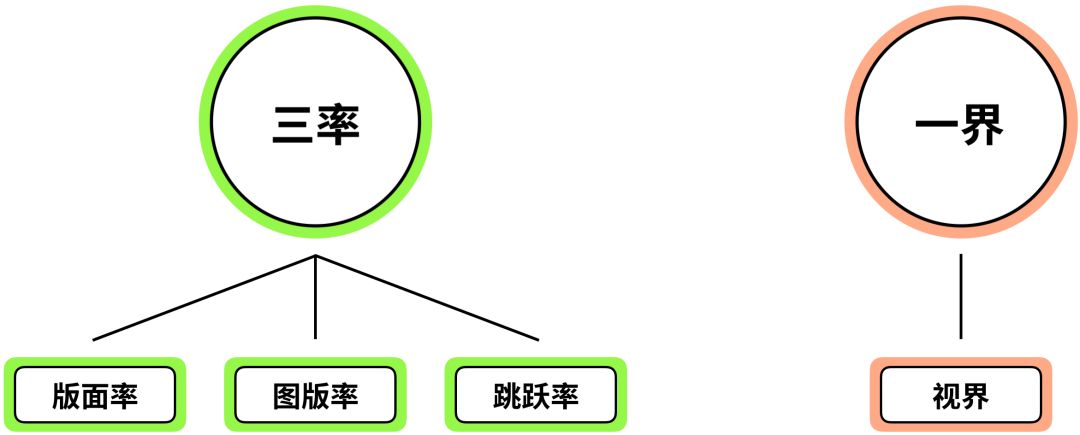
在平面设计中,有三率一界的说法。三率指的是版面率、图版率以及跳跃率,而一界指的是视觉界限,简称视界。今天不谈一界,主要来说说三率。
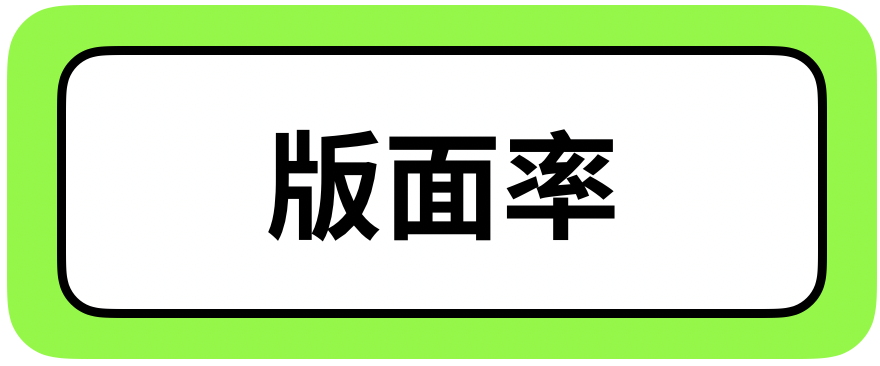
首先来了解一下,什么是版面率。版面我们都知道,是用来承载信息的一个载体。
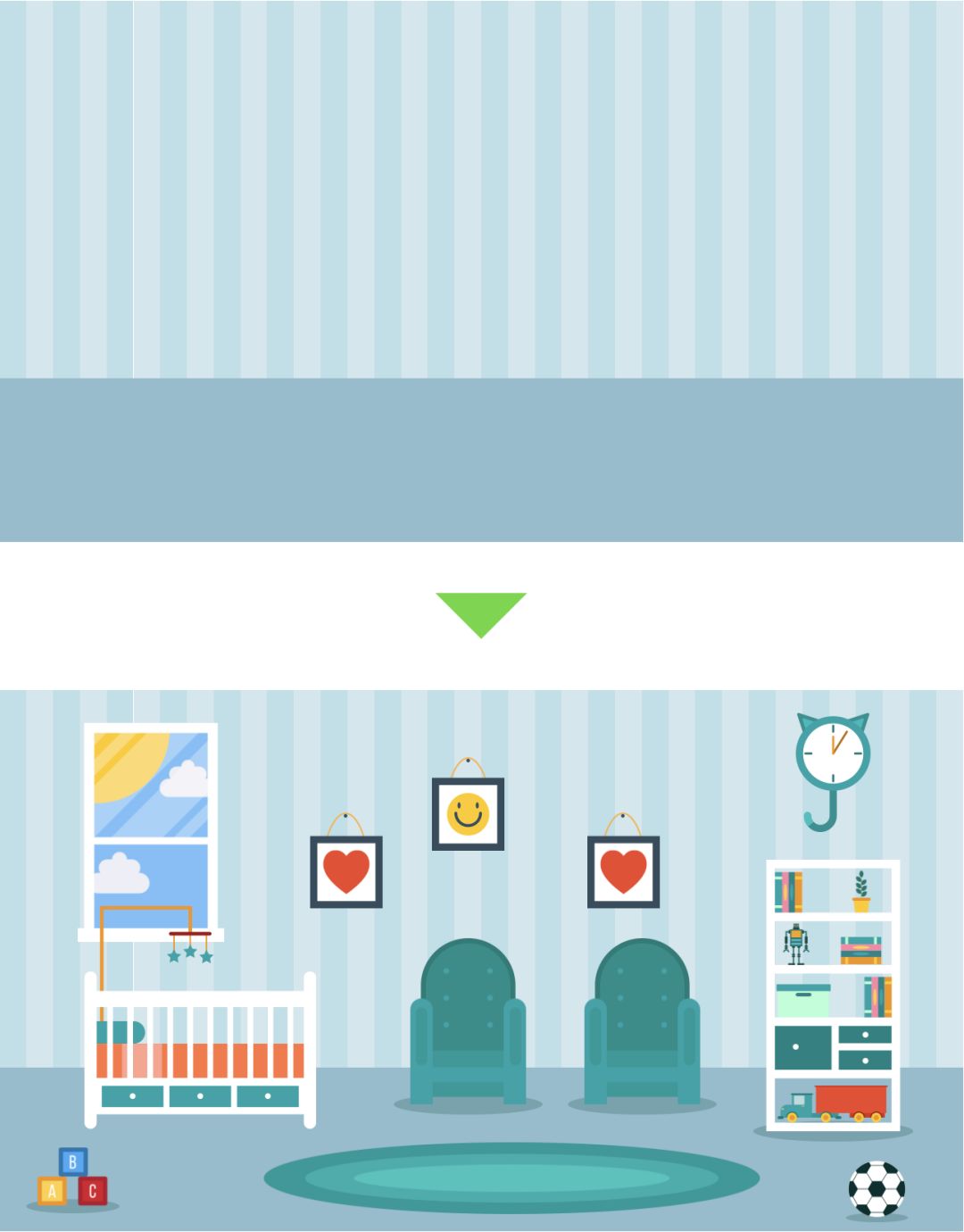
它就像是一个房间,而文字信息与图片素材,则是家具饰品。在合理的情况下,这个房间内放的东西越多,物品占据房间的面积比例也就越高,整个房间的空间被利用的也就越充分。
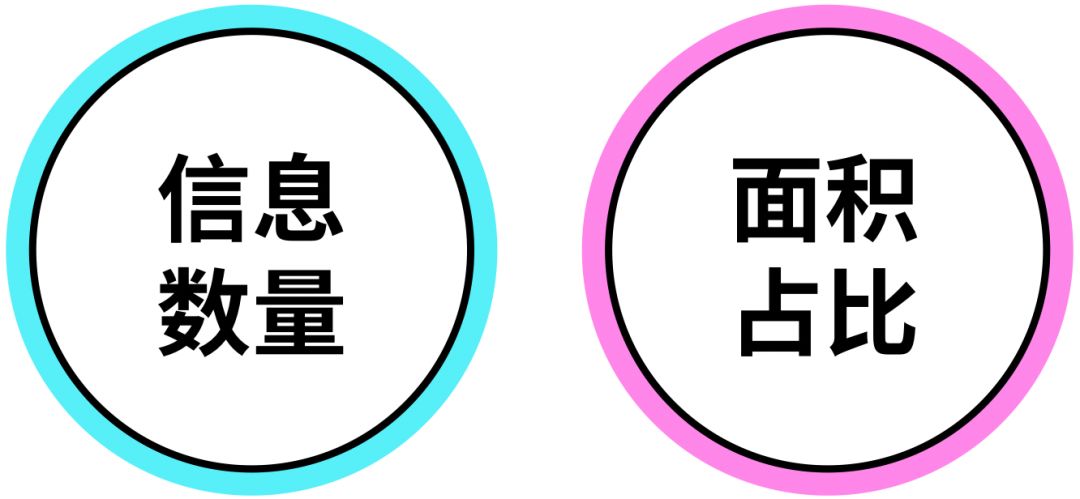
判断一个版面的版面率是高还是低,我们就看版面内部的,信息数量与元素的面积占比即可。
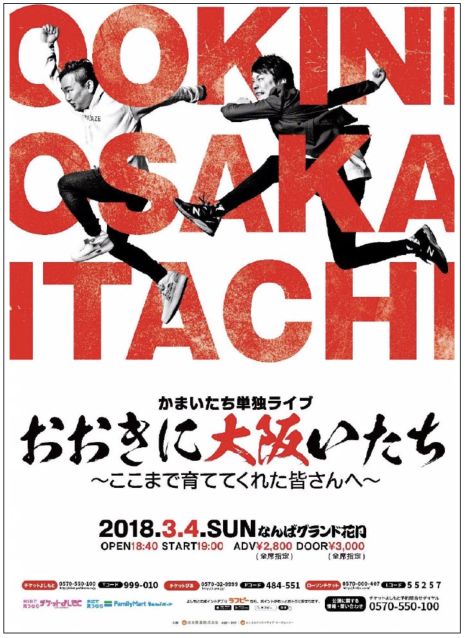
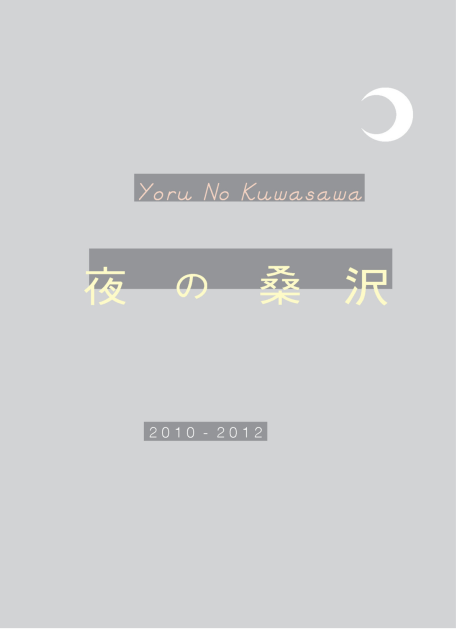
信息量越多,元素的面积占比也就越高,相对的版面率也就越高。信息量越少,元素的面积占比也就越低,相对的版面率也就越低。
不过,数量也不是,唯一的评价标准,关键还得看这些信息,在版面当中的面积占比,为什么这么说呢?
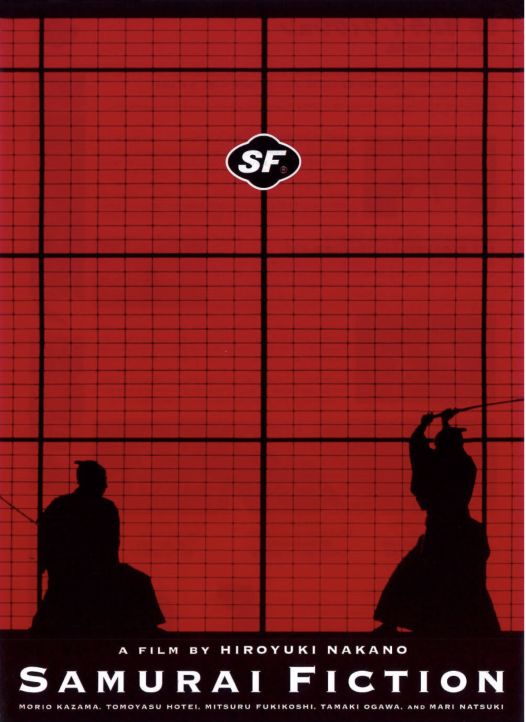
因为,当信息量不多时,只要元素的面积占比够大,版面率依然不会受到影响。跟信息量多的版面比,它们的版面率都是一样的。
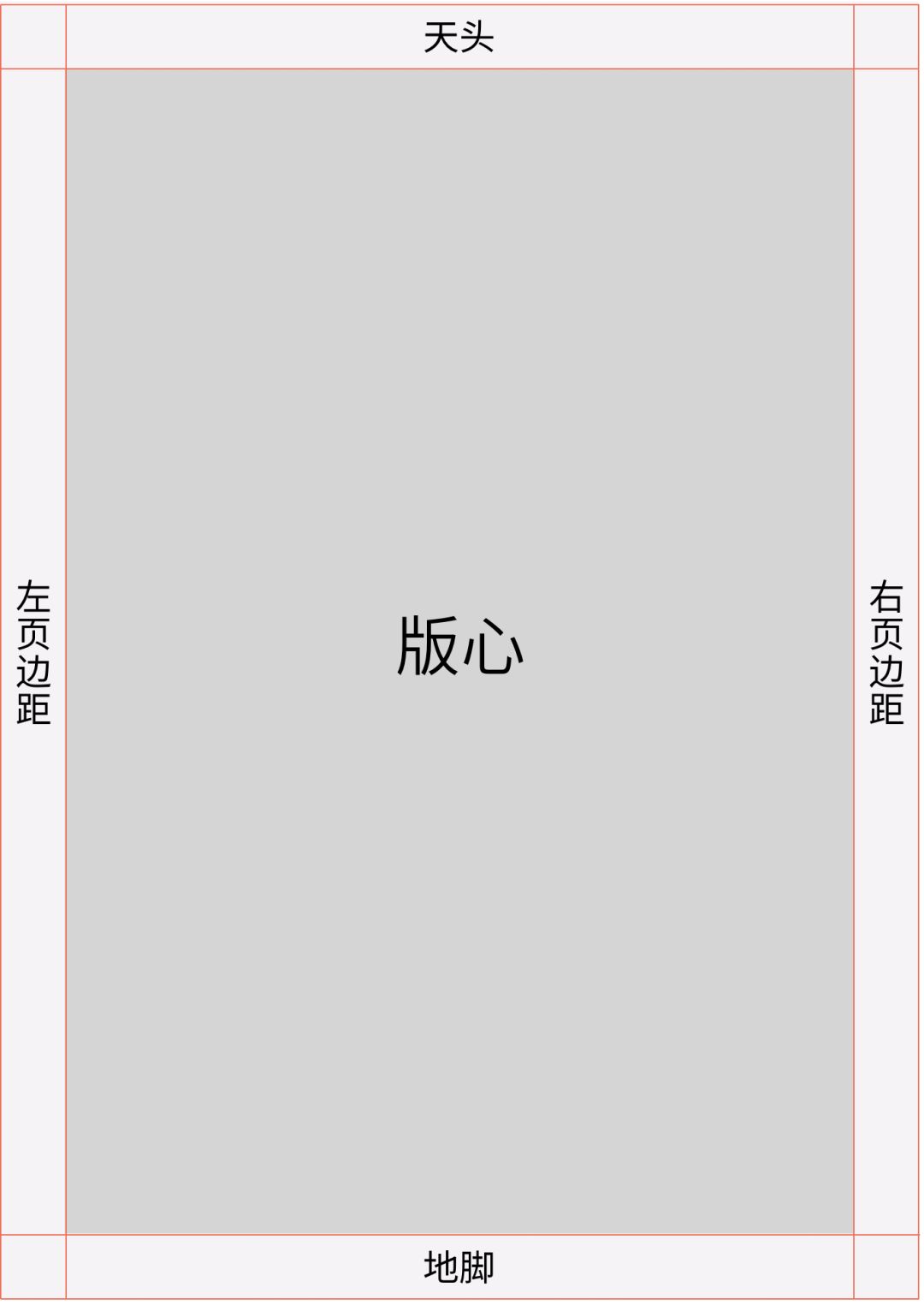
我们都知道,一个版面是存在版心的。除去天头地脚,左右页边距外,剩下的空间就是版心所在的区域了。
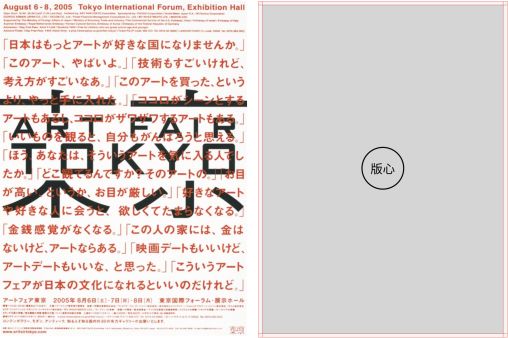
版心的大小会直接影响到,版面率的高低。因为之前也说过了,版面好比是一个房间,你拿一个40平米的房,跟80平米的房比承载量的话,结果可想而知。
除了版心以外,对版面率影响最大的,要数留白了。哪怕你版心定得再大,如果版面内部留白较多的话,版面率还低的。因为留白与元素的面积占比,是成正比的。留白多,元素的面积占比就少,留白少,元素的面积占比就多。
在版心一致的情况下,留白越少版面率越高,留白越多版面率越低。
除了有版面留白以外,还有图片留白。相较于常规的图片来说,那些为了表现清新、安静的图片,会刻意的创造留白来迎合氛围。
在版面率一致的情况下,跟图片留白少的版面比,图片留白多的版面,版面率会显得较低。
版面率越高,画面的视觉张力就越大,版面也会表现的更加活泼与热闹
反之,版面率越低,画面给人的感觉则非常典雅与宁静,版面也会更有格调。
版面率之所以有高低之分,完全取决于你想要传达的气质是什么。当需要表现出,活泼与热闹感时,可以提高版面率。当需要表现出安静、典雅范时,则可以降低版面率。
图版率和版面率的意思相近,版面率说的是,文字与图片占据画面的比例,而图版率说的是,图片占据画面的比例。
如果整个页面都是由图片构成的,那图版率就是100%。反之,如果页面全是文字,图版率则为0%
一般来说,版面中的图片数量越多,图版率也就越高。因为随着图片数量的增加,图片的占比也在增加。
但有一点需要注意的是,跟版面率一样,元素的数量并不是绝对的。要想图版率高,在有数量的基础上,图片自身的面积也不能过小。
哪怕版面中只有一张图片,只要面积足够大的话,图版率给人的感觉,也会比那些数量上占优势的版面要高。
一般来说,图片的视觉冲击力比文字强85%,提高图版率可以活跃版面,但完全没有文字的版面也会显得格外空洞,让人觉得这个版面非常的单调与无味。
当图版率为0%时,观者会丧失阅读的兴趣,因为版面显得非常枯燥。当图版率为40%时,观者的阅读兴趣会随之上升,因为版面充满了生气,富有活力。当图版率为100%时,版面则会给观者带来,强烈的视觉感受。
看到这,我相信不用分析大家也知道了,图版率高的版面,会给人带来活跃与热闹的印象。
相反,图版率低的版面,则会给人带来一种,非常安静与沉稳的印象。
当然,也不是说图版率高,版面就一定会传达出活跃与热闹的氛围,如果图片属于安静、有格调的类型的话,提高图版率只会放大图片自身的气质。
现在很多奢侈品,比如:珠宝,手表,香包等等,无论是电视广告还是纸媒广告,都采用大图版率,有故事内容的情境图,来创造氛围,好吸引消费者的目光,从而促进产品的销售。
当遇到特殊情况如:图片的像素不高,或是尺寸受限无法放大时,要怎么提高图版率呢?针对这个问题,我给大家介绍三种解决方法。
在演示之前,先跟大家说明一下,这三种方法属于视觉上的提高,并非实质上的。
第一种方法为:填充底色,也就是背景色、第二种方法为:添加图形做叠底、第三种方法为:重复这张图片或是图形,通过增加图片数量的方式,来使图片的面积占比变高。
首先,我们先来看看第一种方式:填充底色。做法非常简单,选取一个与自身图片相契合,或是跟图片中的主色系,相对比、相互补的颜色进行填充即可。
现在我们所看到的这张海报中,有三个色彩分别为:黄色、深蓝色与黑色。从中选取一个出来用作填充,这叫相契合
选出图片中的主色系,然后在结合色相环找出,跟这个主色系,有“对比”关系的色彩用作填充,这叫相对比。
这张海报的主色系是黄色,而跟黄色有对比关系的色彩为:红色与蓝色。
相互补,意思就是挑选一个,跟主色系相“互补”的颜色进行填充。而跟黄色有互补关系的色彩是“紫色”。
不管是相契合,还是想对比或是相互补,它们之间没有优劣之分,具体要用哪个,可结合实际的视觉效果来做决定。
对比一下可以看出,填充底色后图版率跟之前比,显得要高不少。而且,填充底色还有一个好处就是,可以烘托版面的氛围。
拿这个案例来说,背景色改成黑色后,版面整体的视觉效果,比白色背景的要好,版面整体的氛围也上来了。
这些是通过填充底色,来改善图版率低印象的海报案例。
第二种方式:置入图形做叠底。大家可以根据自身项目的气质,来选择一个合适的图形做叠底。
假设,现在在这个画面中,人物只能放这么大,但是,我们又想提高图版率。
这时,可通过图形叠底的方式,来增加图片的面积占比提高图版率。它跟填充底色不同,如果说,填充底色是视觉上的提升,那图形叠底则更实际一些。
这些作品全都是通过,叠加图形来增加图版率的。
除了叠加图形以外,还可以叠加文字。因为文字也算是图形的一种了,而用来提高,图版率印象的文字,会舍弃掉部分识别性,仅做为单纯的底纹来使用。
这些是通过叠加文字图形来增加,图版率的海报。
第三个方式:使用重复的技法。关于重复我们订阅号之前也出了一篇教程了,虽然讲的是文字重复,但运用在图片或是图形上,效果都是一样的。
跳跃率跟版面率与图版率不同,说的就不是占比的事了。那跳跃率指的到底是什么?又是如何产生的呢?
要想创造出跳跃率,首先就要有对比,有对比才有起伏,有了起伏才能产生跳跃率。
在版式设计中,跳跃率指的就是:元素间的大小对比。元素间的大小差距越显著,跳跃率也就越高,元素间的大小差距越小,跳跃率也就越低。
当版面中出现多个大小对比时,要如何判断跳跃率,是高还是低呢?这时只需找到版面中,最大的元素与最小的元素即可,看看它们之间的差距是大还是小。大跳跃率就高,小跳跃率就低。
而在版面中,能出现大小对比的只有图片(图形)与文字信息了。也就是说,跳跃率分两种:一种为图片跳跃率,另一种为文字跳跃率。
首先,我们来看看图片跳跃率。当版面中只有一张图时,是不存在图片跳跃率的,只有出现两张或两张以上时才有。
之前也说过了,想要创造出跳跃率,就要产生大小对比。那谁应该被放大,谁又应该被缩小呢? 下面,我给大家提供几个图片放大的思路。
一、包含人物的图片,首选放大。因为,按照图片的吸引力度来分,人物类图片排在第一位,接着是动物类图片,再往下是美食、风景类等图片。
这是放大人物图片的画册例子
二、图片内部人物,或是物体较多的图,首选放大。因为越是丰富的图,其细节也就越多,缩小后,不利于展示这些细节。
这是放大物体较多图片的画册例子
三、存在差异性的图片,首选放大。这个概念源于特异构成。当全是一致的元素中,出现了一个不一样的元素时,这个存在差异性的元素,就是最吸引人的。
这是放大存在差异性图片的画册例子
四、特写图首选放大。因为跟全景图比,特写图的视觉冲击力更大,能更好的吸引读者的视线。
这是放大特写图片的画册例子
为什么说,特写图比全景图的视觉冲击力强呢?因为,特写图的视觉面积就要比全景图大,放大特写图时,图片的跳跃率也会显得比,放大全景图的版面要高。
特写图首选放大也不是绝对的。如果全是特写图,只有一张全景图的话,就要放大全景图了。
因为跟哪些特写图比,这张全景图就是有差异性的那个。所以希望大家能够活学活用,不要钻牛角尖。
如果,图片的内容与性质都差不多的话,这时就没什么好选的了,放大哪个都行,或者等大也是可以的能保持统一性。
在海报设计中,这种类型也是最常见的。
图片跳跃率高的版面,视觉冲击力强富有活力。
图片跳跃率低的版面视觉冲击力能弱一些。
与版面率、图版率一样,图片跳跃率也要考虑到,图片自身的气质。如果图片看起来就是静的,那版面的视觉冲击力则会弱一些。
文字跳跃率,说的就是字号大小对比的事了,按照信息的重要程度,来设置不同的字号大小关系。与图片跳跃率不同,文字跳跃率在版面中扮演着很重要的角色,因为它将直接影响到,文字信息的传播效率。
没有文字跳跃率,信息会变得难以阅读,读者在第一时间内,也找不到信息中所描述的重点是什么。
设置字号大小对比时,有两个原则要遵守,第一个是:对比不能模棱两可,第二个是:对比不能过于极端。
对比不能模棱两可,意思是:两个相邻且存在对比的字号之间,大小不能过于接近,过于接近的话就属于无效的对比了。
而对比不能过于极端,意思是:两个相邻且存在对比的字号之间,差距不能过于悬殊。因为这样会导致文字组看起来很不协调,也就是说会影响到大小对比的平衡性。
这个时候我们可以再追加几个过渡层的文字信息。因为组合中除了最大和最小的文字以外,还要有一个中等大小的文字,用于抵消对比过大导致的不平衡问题。
如果拿捏不准确,文字到底要放大或是要缩小多少时,推荐大家使用:等差数列、等比数列,或是斐波那契数列来辅助进行设置。
等差数列,按照不断+1的方式进行增长。在运用时,我们可以随便选取一个数值,来进行字号的缩放。
假设小字号为30pt,大字号为60pt,这时的字号比例为1 : 2,也就是说大字号是小字号的2倍。当大字号为90pt时,字号比例就是1 : 3,大字号是小字号的3倍。想大几倍就乘以几,想小几倍就除以几。
这个时候就可以使用之前讲过的,在图片尺寸受限的情况下,通过叠加图形的方式在视觉上提高图版率。
置入标题信息,在编排的同时将上方的书脊也一同编排出来。标题信息多重复几次,因为文字跳跃率有限制字号不能太大,但作为标题来说必须要是醒目的,而重复出现可以提高视觉面积,变相的来说视觉面积高了,醒目度也会跟着提高。
接着,将腰封以及下方的书脊部分编排出来。
在挑选一些重要的信息换上色彩。
最后,在腰封组合的负空间处置入几个小恐龙,用于提高版面的图片跳跃率。到此最后这个案例,也就设计完成了。
不管是版面率、图版率还是跳跃率,它们的高与低都由,画面所要传达的感觉和项目自身的气质所决定的。而这三大率也是我们使用「工具」的技巧与方法。我相信下次再遇到编排问题时,大家不会像以前那样没有底气了。图片应不应该缩小,文字应不应该放大心中早有定夺。工欲善其事必先利其器,「器」要怎么用已经告诉大家了,而「事」能不能做好,就要看个人平时的努力程度啦,多看多练都是必要的。好了本期的教程就到这里,我们下期再见啦。